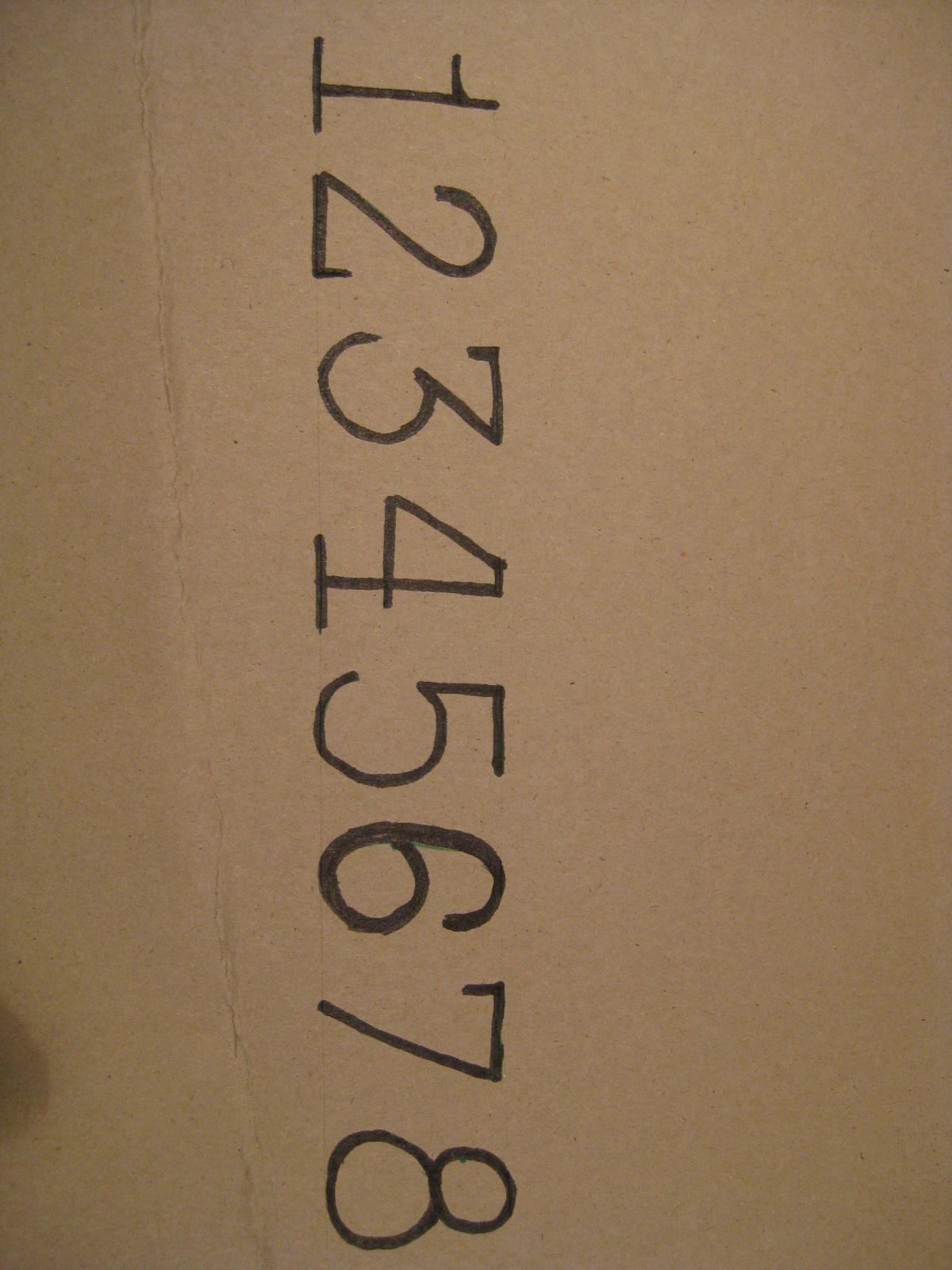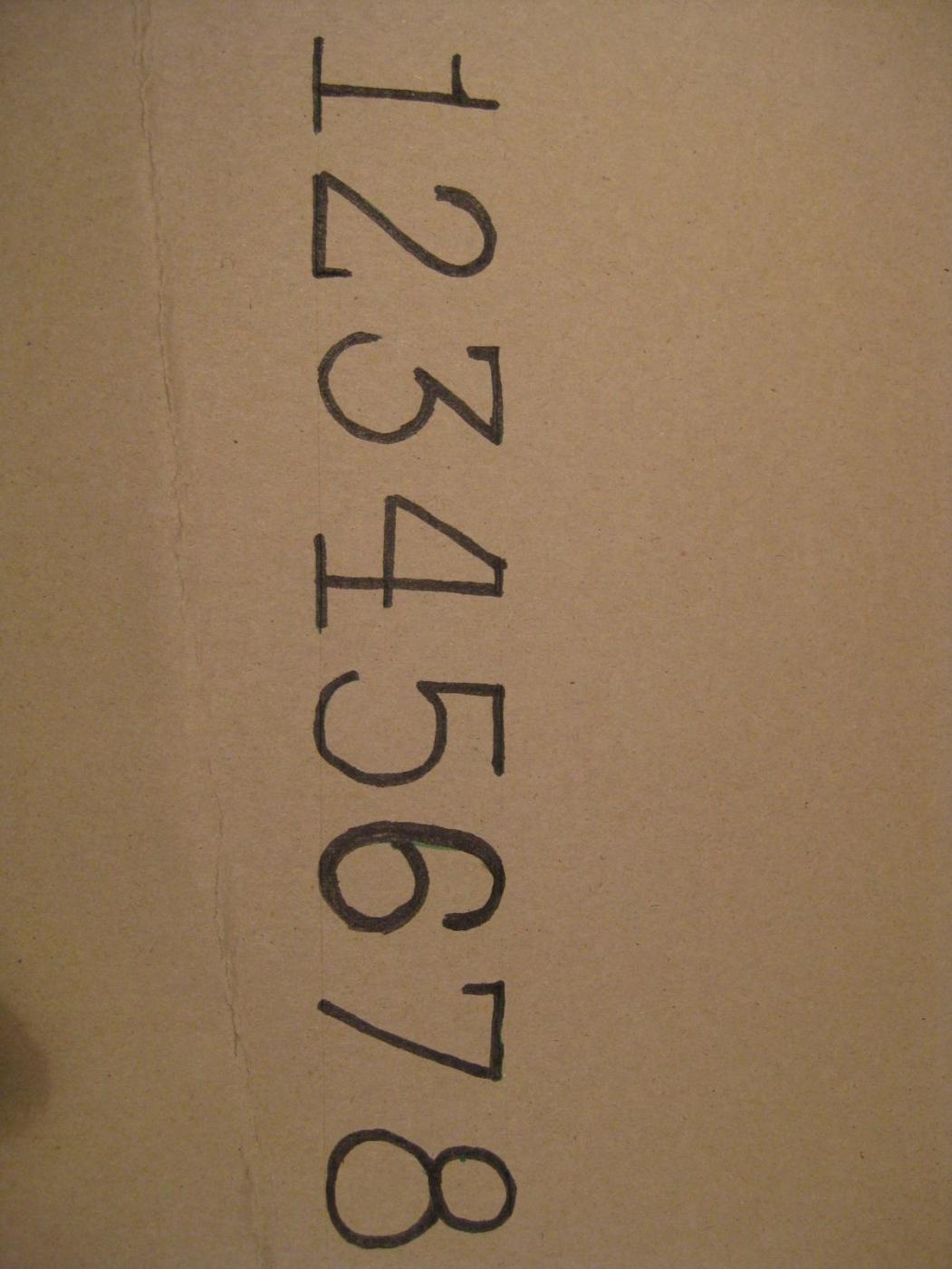
Schrifttype alter Schlagzahlen
... dann hätte ich gleich noch eine Frage:
Desöfteren habe ich auf Werkteilen und Typenschilden den abgebildeten Serifen-Schrifttyp von Schlagzahlen gesehen. Da die oft rostig, verschlagen und selten vollständig sind, habe ich sie mal  alle nebeneinander aufgezeichnet. Sie stammen aus dem deutschspachigen Raum und wurden auf jeden Fall vor 1945 benutzt.
Auch hier wirst du keine befriedigende Antwort bekommen. Der »Font« eines (alten) Schlagzahlen-Satzes ist der Satz selber. Das sind die verkäuflichen Buchstaben, die speziell so für diesen Zweck angefertigt wurden. Da gibt es nichts anderes. Weder stellen die Schlagzahlen eine bestimmte andere, benennbare Satzschrift dar, noch gibt es heute Fonts, die so ein altes Schlagzahlenset vernünftig nachempfinden.
schade, ich hatte gedacht (und in Deutschland fast erwartet!), dass sowas geregelt war und ist. Zumindest heute gibt es für Schlagzahlen das Schriftbild nach DIN 1451 - übrigens völlig anders gestaltet und durchaus hässlich, nach meinem Empfinden.
Im übrigen stellen die Hersteller von Schlagzahlen auch heute noch individuell entworfene Sätze für ihre Kunden her, Nämlich um so die Fälschung von Seriennummern zu erschweren.
Ja,  so einen Anbieter gibt es in den USA, der für $185 einen Satz Schlagzahlen jedweder Konfiguration herstellt,  CNC-fräst und härtet. Irgendwie toll und zugleich auch besorgniserregend, wenn man halt an das Thema Fälschungen denkt.